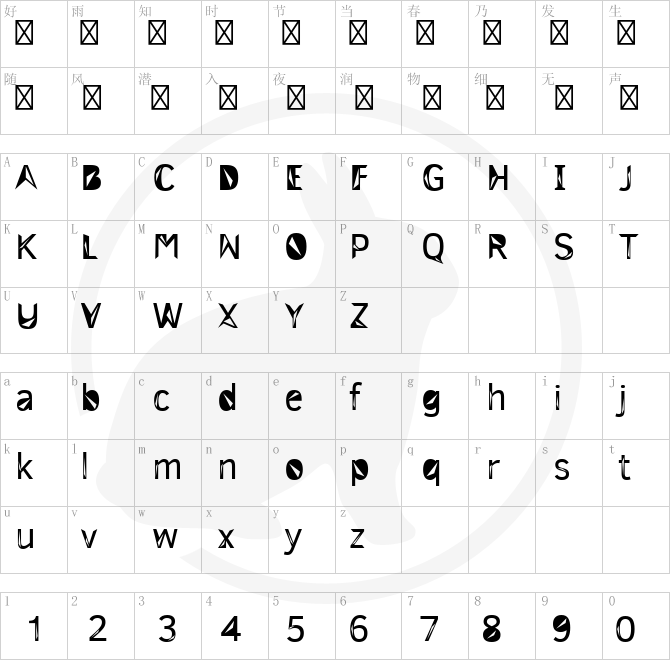
3M Trislan.ttf字体下载,这款字体结构工整、笔画清晰,兼顾美观与易读性,适用于标题、正文、海报、包装、LOGO 等多种场景。字形优雅稳定,风格百搭耐看,适配日常排版与创意设计,让文字呈现更舒适、更具质感。3M Trislan.ttf字体下载一笔一画,皆是细节,以均衡的比例、流畅的线条打造舒适视觉体验,字形端正大气,风格简约现代。无论是商业设计、品牌宣传还是日常排版,都能轻松驾驭,让文字更有格调与力量。3M Trislan.ttf字体下载字体下载。